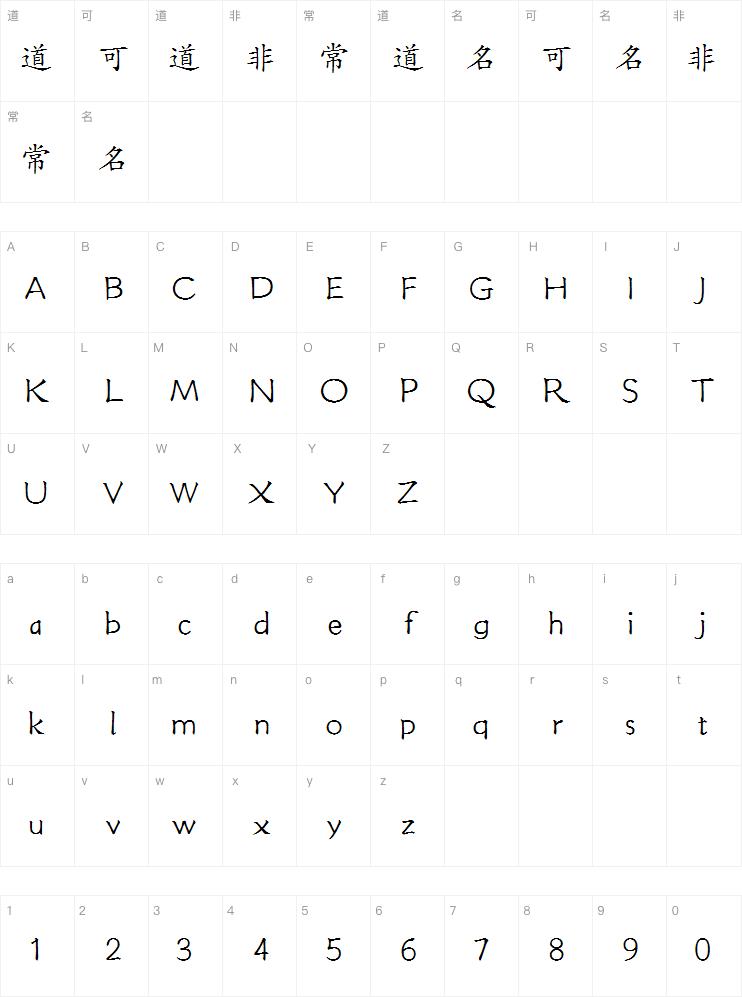
方正楷体
方正楷
方正楷体源于上海印刷技术研究所“华文楷体”字稿。原“华文楷体”诞生于20世纪40年代,新中国成立后一直是主要使用的铅字楷体。在此期间,上海字模一厂、上海印刷技术研究所等单位进行了数次改良,并添加了简体字。方正楷体的结构秀丽匀称,笔画圆润柔和,横竖笔画的粗细变化不大。这款字体被大量应用于报纸、杂志和书籍中的正文,在教科书中最为常见。
方正楷体